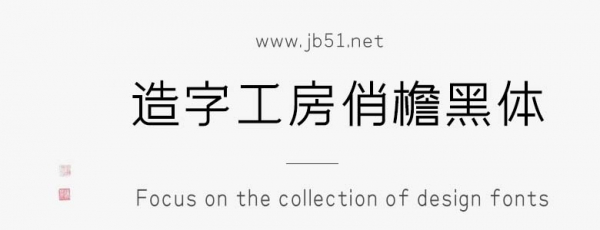
造字工房俏檐黑體由上首造字字庫出品的字體,字體由傳統(tǒng)黑體衍生而來的全新字體,部分收筆處向上揚起的俏角,如中式建筑中翹起的屋檐,適合應(yīng)用于平面宣傳設(shè)計、網(wǎng)頁設(shè)計,書法字帖等領(lǐng)域,需要的朋友可以前來本站下載。
造字工房俏檐黑體是一款由傳統(tǒng)黑體衍生而來的全新字體。筆畫細致瘦長,字形方正端莊,部分收筆處向上揚起的俏角,如中式建筑中翹起的屋檐,字體纖細輕盈、靈巧活潑。本字體為簡體字庫,采用OpenType/CID格式,Adobe-GB1-5編碼。基于中華人民共和國GB2312-80字符集標準,另按需添加101個漢字。共收容字數(shù)6864CJK漢字,ASCII常用字符100個。